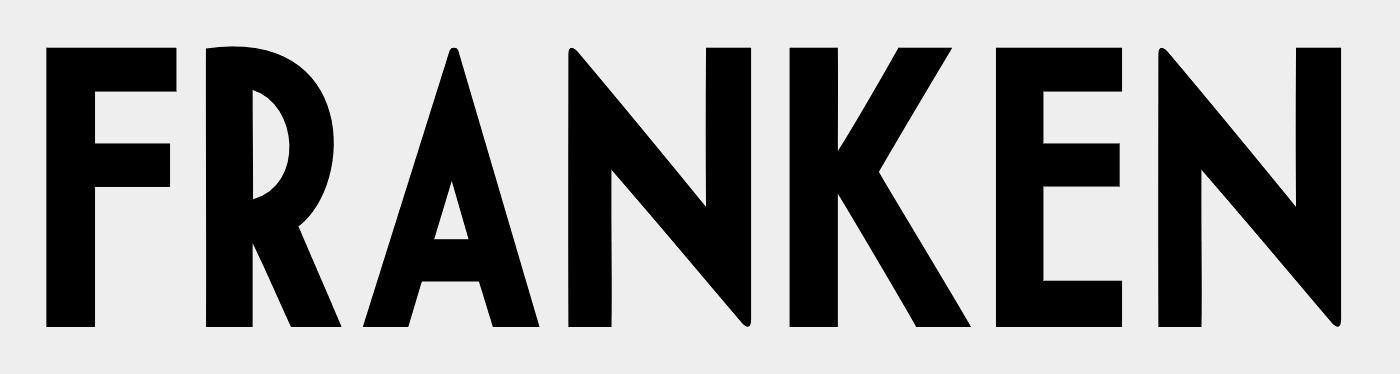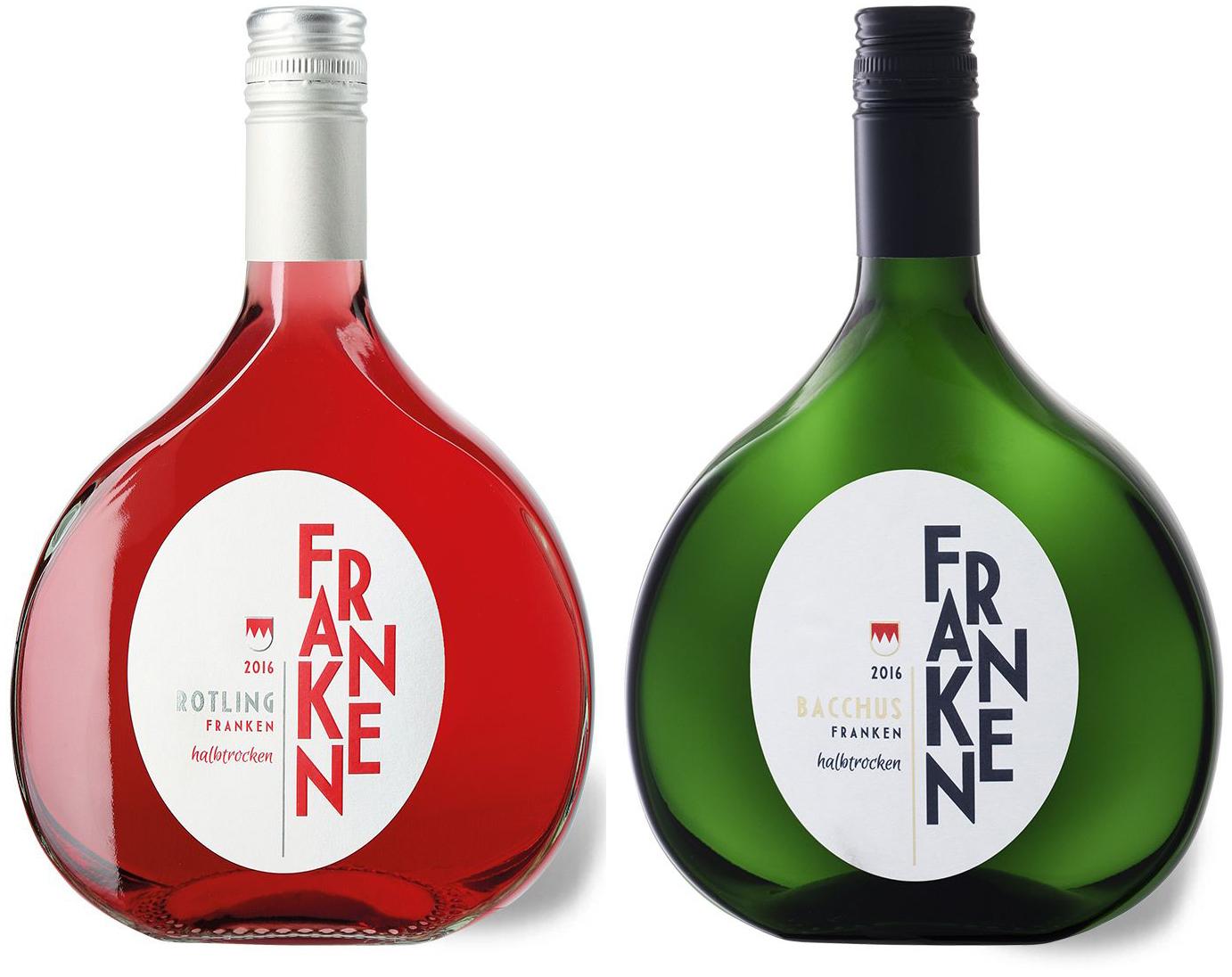
Schrift der Flasche "FRANKEN" Bacchus halbtrocken
im Lidl-Prospekt sah ich heute die Abbildung einer Flasche, gefüllt mit einem halbtrockenen Bacchus aus Franken.
Die Serifelnlose ähnelt der PENATEN-Schrift, welche ich vor kurzem suchte.
Allerdings ist das "R" doch unschön und ungestalt in seinem oberen Teil des Bogens, finde ich.
Weiß jemand, wie die Type heißt? - Sie ist wohö eher modern... oder?